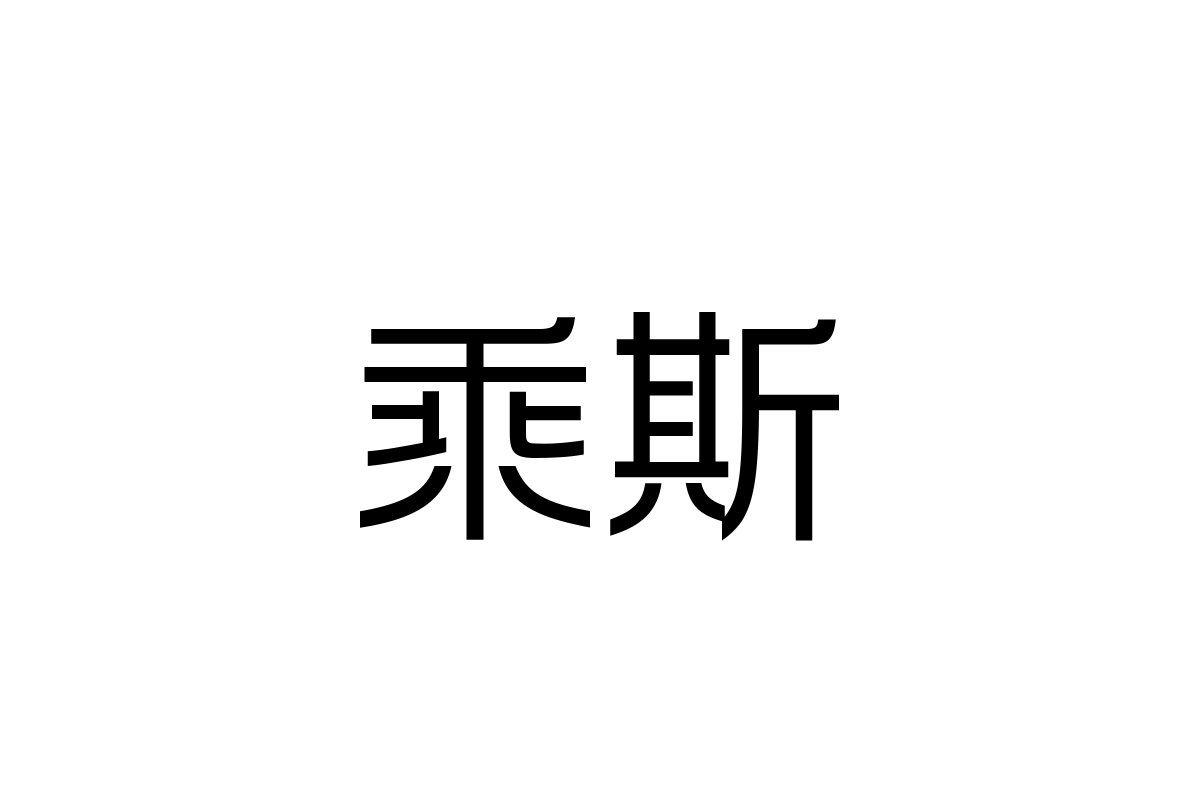
汉仪风尚黑B5-45是一款现代简约风格的中文字体,具有清晰、易读的特点。这款字体采用了简洁的线条和结构,使得整体看起来更加干净利落。同时,它的大小适中,适用于各种类型的文本排版,无论是标题、正文还是广告宣传等场景都能轻松驾驭。
此外,这款字体还具有一定的艺术感,通过不同的笔画和组合方式,展现出独特的视觉效果。这使得它在设计中能够更好地吸引观众的注意力,提升整体的美感。
总之,汉仪风尚黑B5-45是一款非常实用的中文字体,适合用于各类文字排版工作。